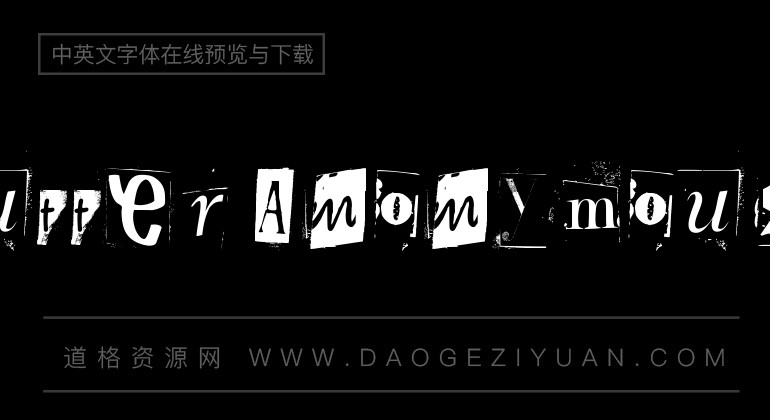
Woodcutter Anonymous Part 2是一种装饰性的字体,它的风格很有特点,可以让文字看起来像是手工雕刻而成的。它的笔画宽度不一,有些地方是粗重的,有些地方则非常细小,这种不规则的线条非常适合用于海报设计、广告标语或其他需要突出视觉效果的场合。此外,Woodcutter Anonymous Part 2还带有一些独特的装饰效果,如细小的点、线条或花纹,这些装饰元素使得文字更加有趣和引人注目。内容介绍
Woodcutter Anonymous part 2是一款非常不错的手写艺术字体,具有很好的视觉感,适合于文化类的宣传设计、商业类品牌的广告和产品包装设计以及个性化文字排版等较多场景。